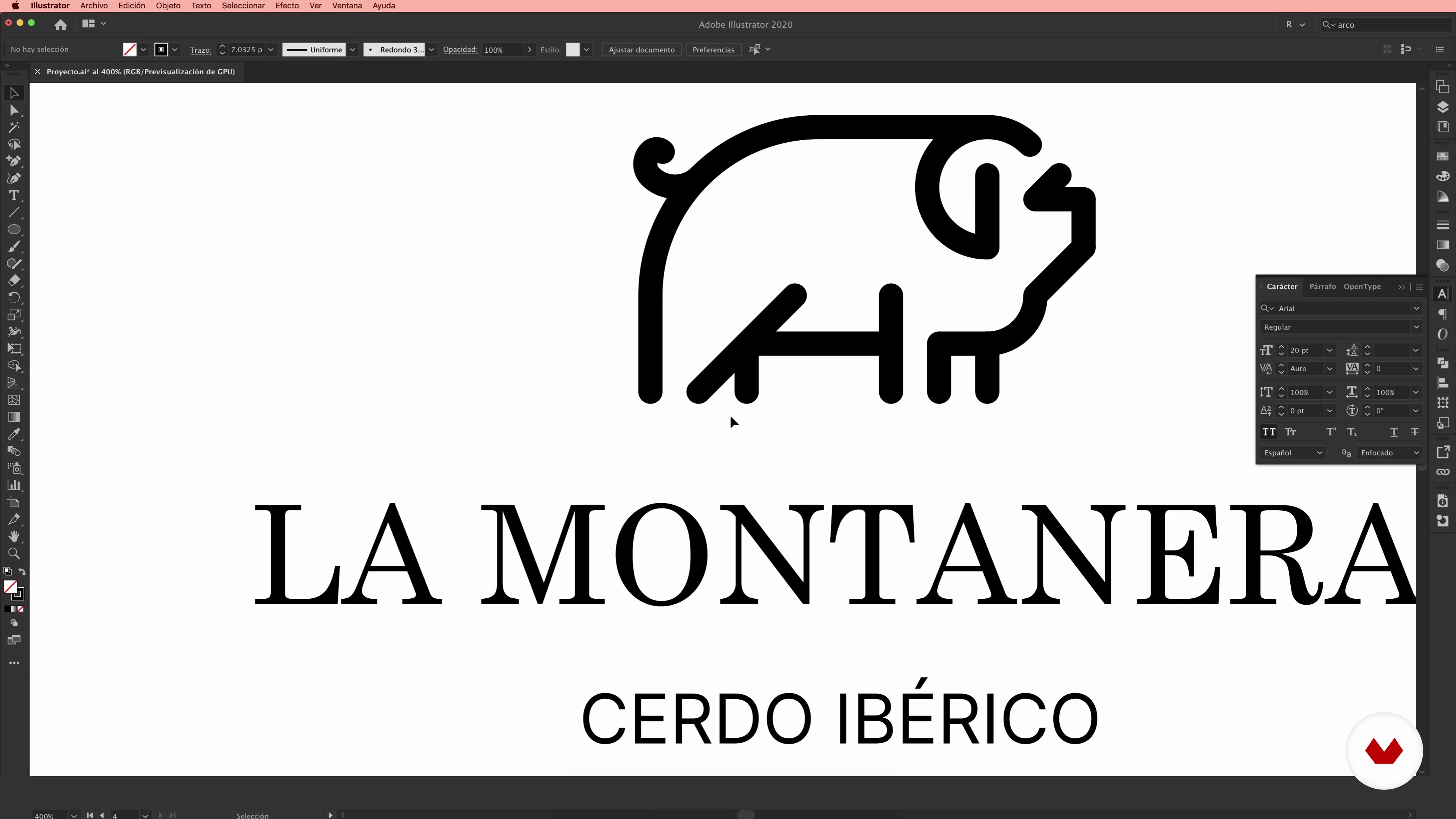
Typografia
O lekcji wideo: Typografia
Podsumowanie
“Teraz, gdy nasze zwierzę mamy gotowe, czas wybrać źródło, które będzie mu towarzyszyć. W tej lekcji przyjrzymy się klasyfikacji krojów pisma i podpowiem, jakie rzeczy należy wziąć pod uwagę przy wyborze najodpowiedniejszego dla swojego projektu. Dodatkowo podam kilka wskazówek, jak w razie potrzeby dokonać poprawek oraz podpowiem, jak dostosować lub dopasować część typograficzną do symbolu.”
Na tej lekcji wideo Rubén Ferlo porusza temat: Typografia, która stanowi część kursu na platformie Domestika: Projektowanie logotypów: synteza graficzna i minimalizm. Zacznij projektować zapadającą w pamięć tożsamość marek poprzez oryginalny i prosty proces twórczy.
Częściowa transkrypcja wideo
“Typografia W tej lekcji omówię klasyfikację typów. Powiem Ci, jakie rzeczy musisz wziąć pod uwagę aby wybrać odpowiednią czcionkę do swojego projektu. Zobaczmy. TYPOGRAFIA Selekcja typograficzna może wpływać na naszą tożsamość na lepsze lub gorsze. Wartości przekazywane są poprzez typografię i kolor jako osobowość, siła czy ruch, i źle dobrana czcionka możesz przekierować wiadomość, którą chcesz przekazać. Chcę Ci powiedzieć, że krój i czcionka to nie to samo, chociaż ludzie często używają ich zamiennie. Typografia to zbiór znaków które mają wspólne cechy lub aspekty projektowe, na przykład...”